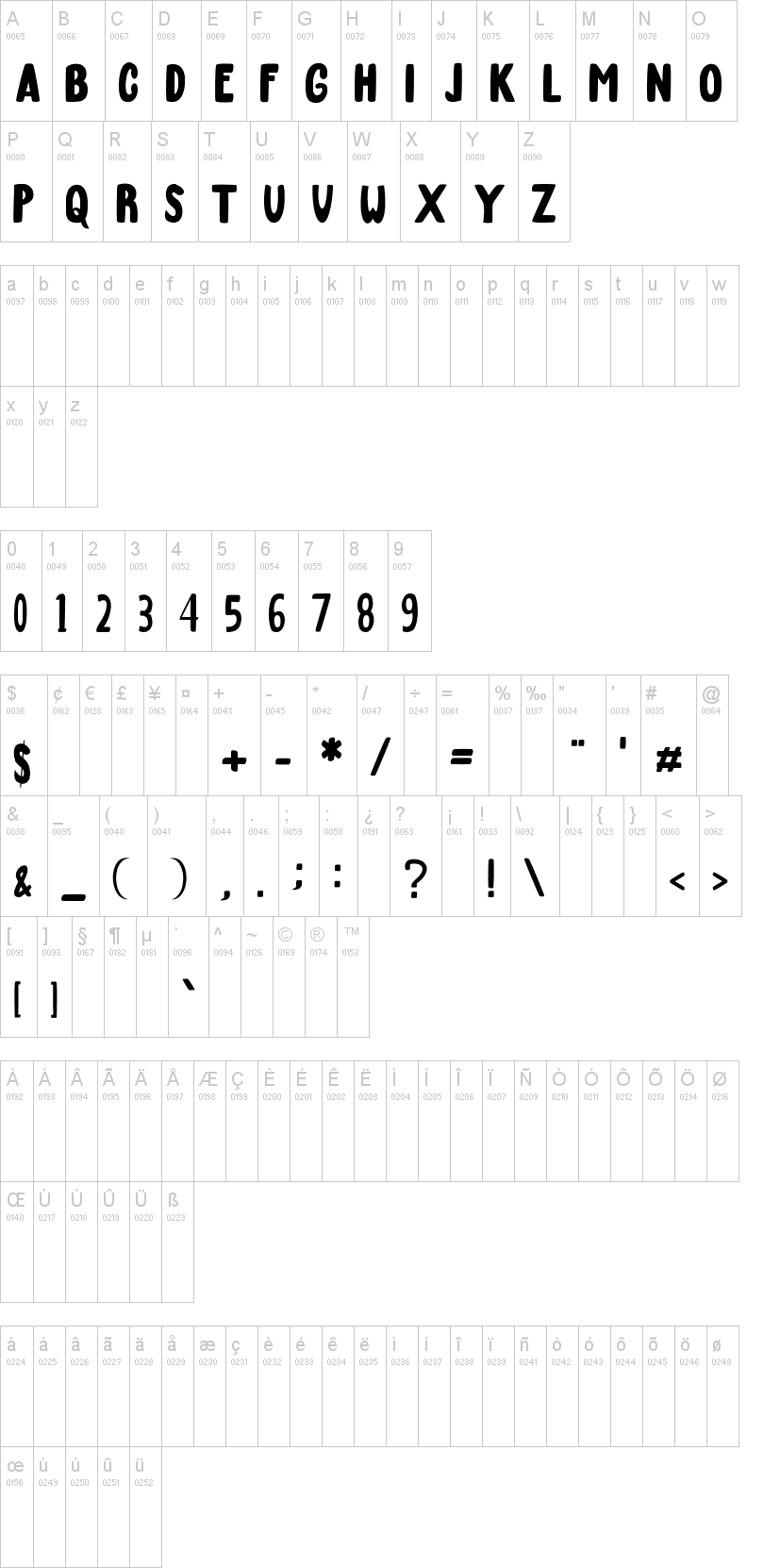
March
March 字体是一款由 Fontfabric 公司设计的一款复古系列字体,它的特点是具有现代感的复古风格,可以为设计师提供更多的创意灵感。March 字体具有清晰的结构,让设计师可以更轻松地进行文本设计。它还具有更多的细节,可以帮助设计师更好地表达他们的想法。它还具有多种字体,可以满足不同的设计需求。
March是一款非常不错的手写艺术字体,具有很好的视觉感,适合于文化类的宣传设计、商业类品牌的广告和产品包装设计以及个性化文字排版等较多场景。